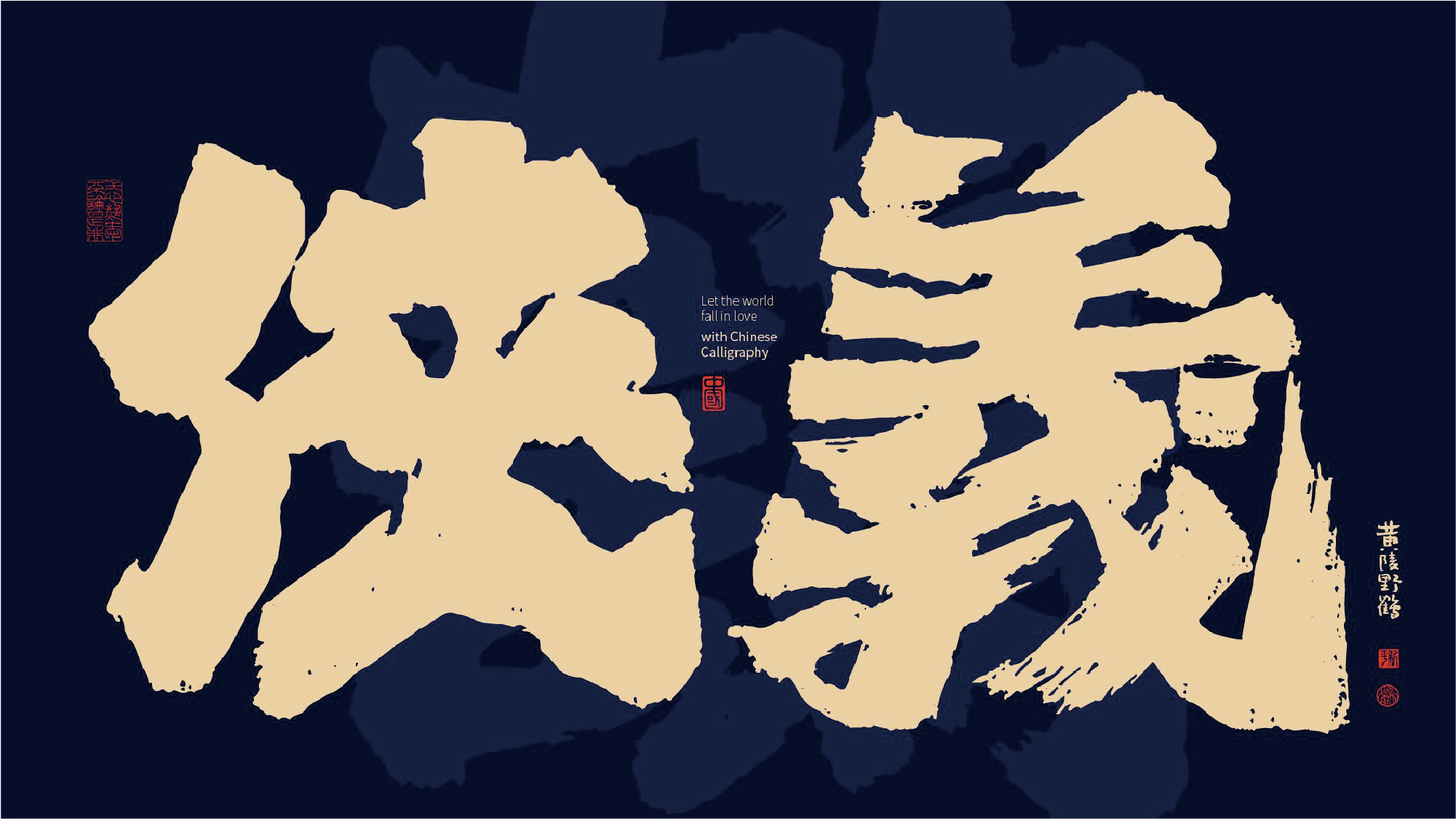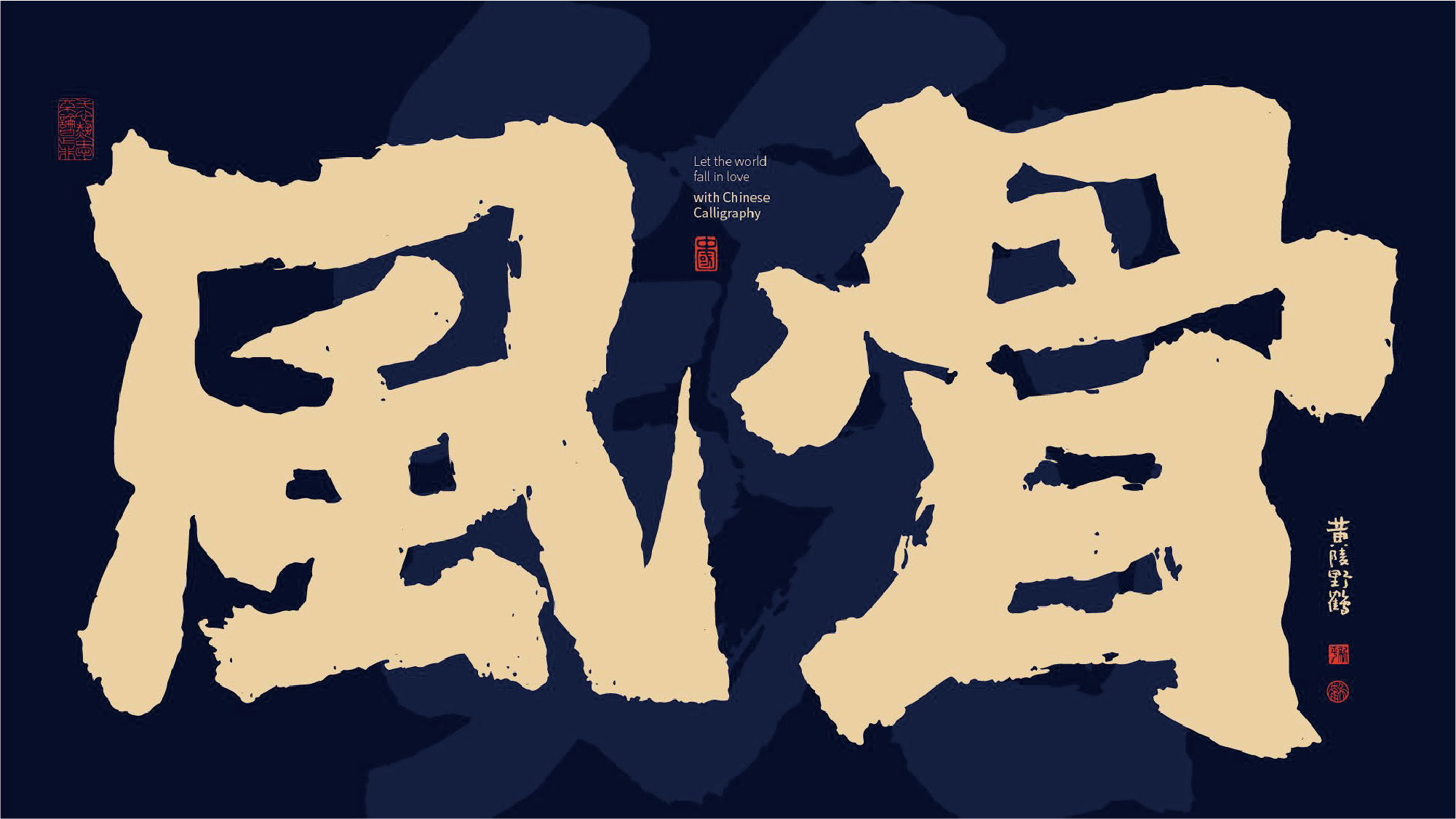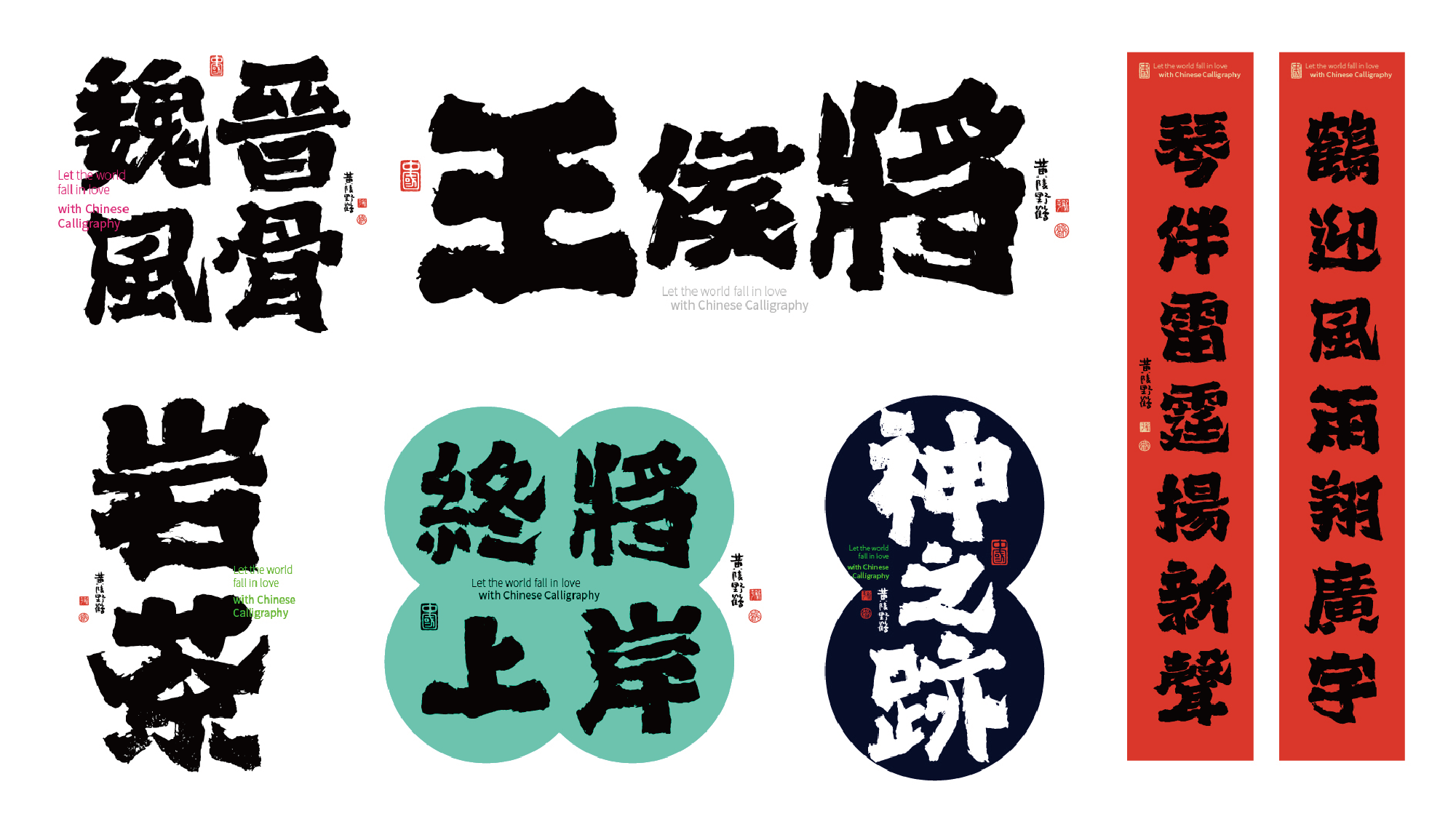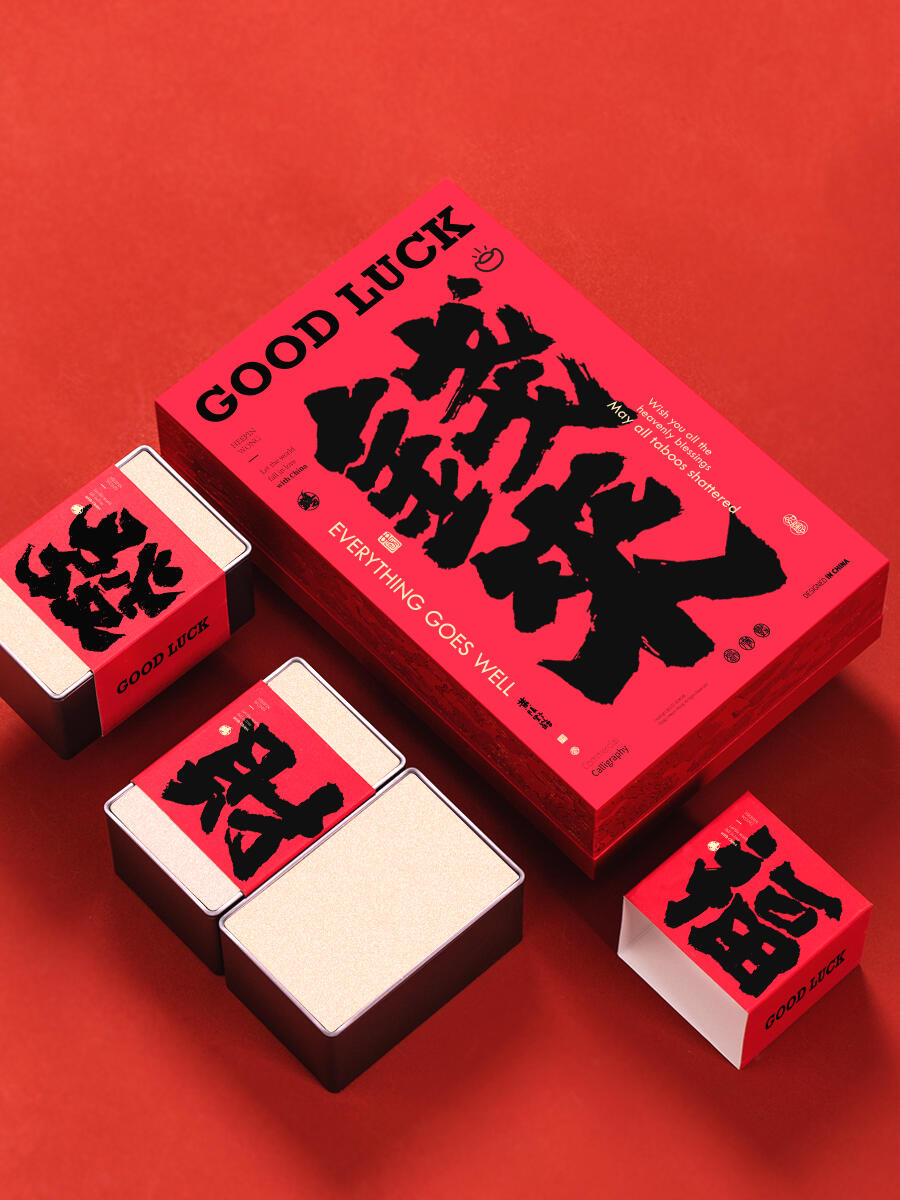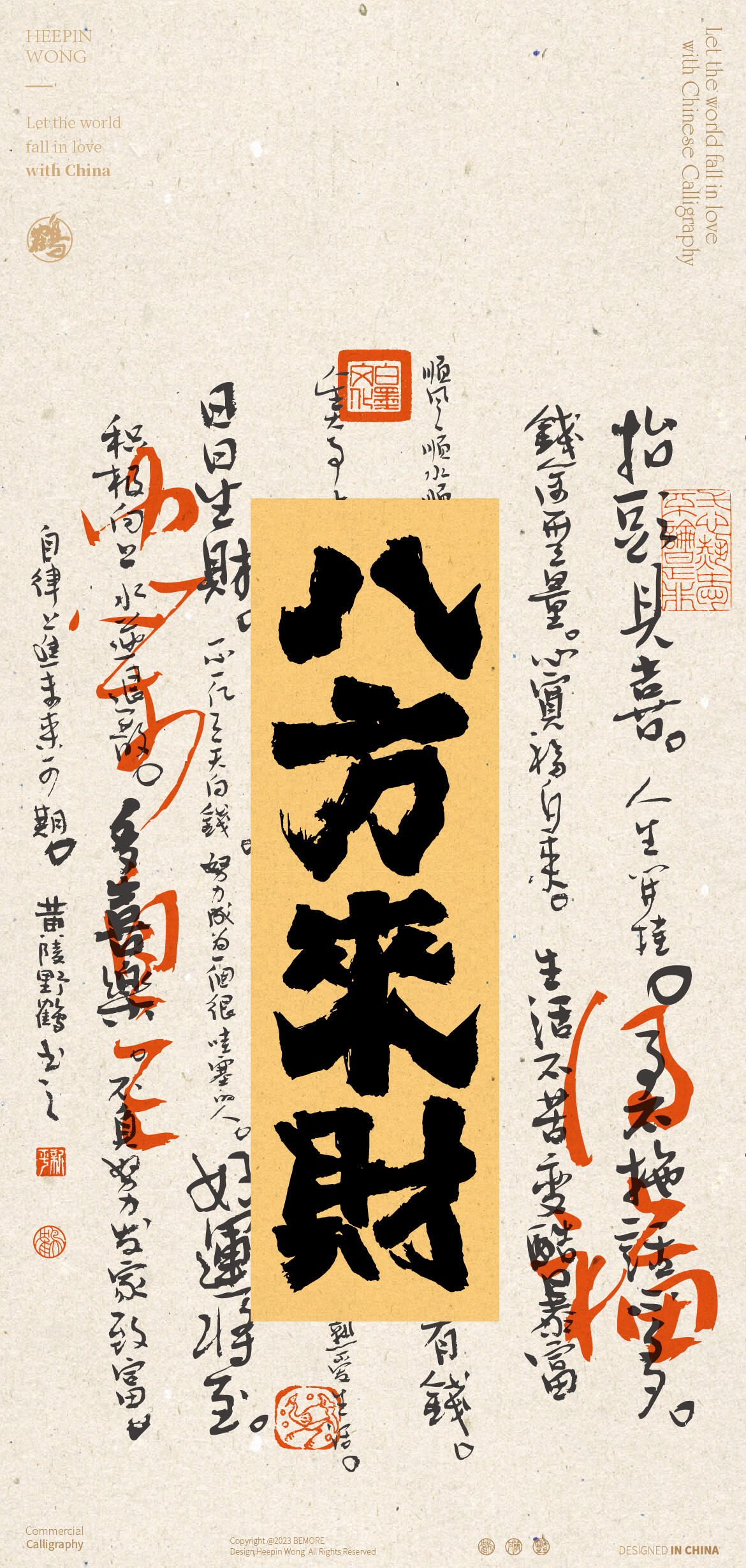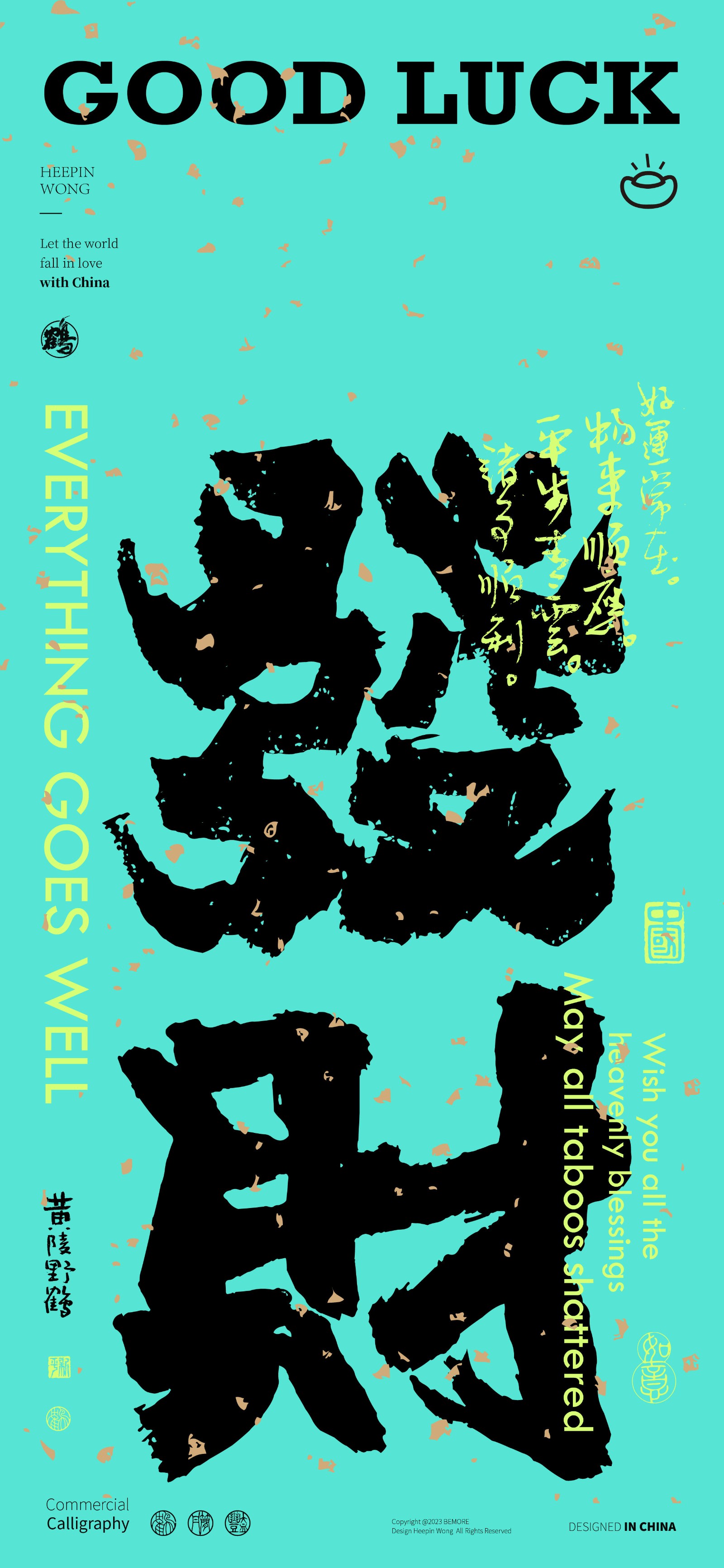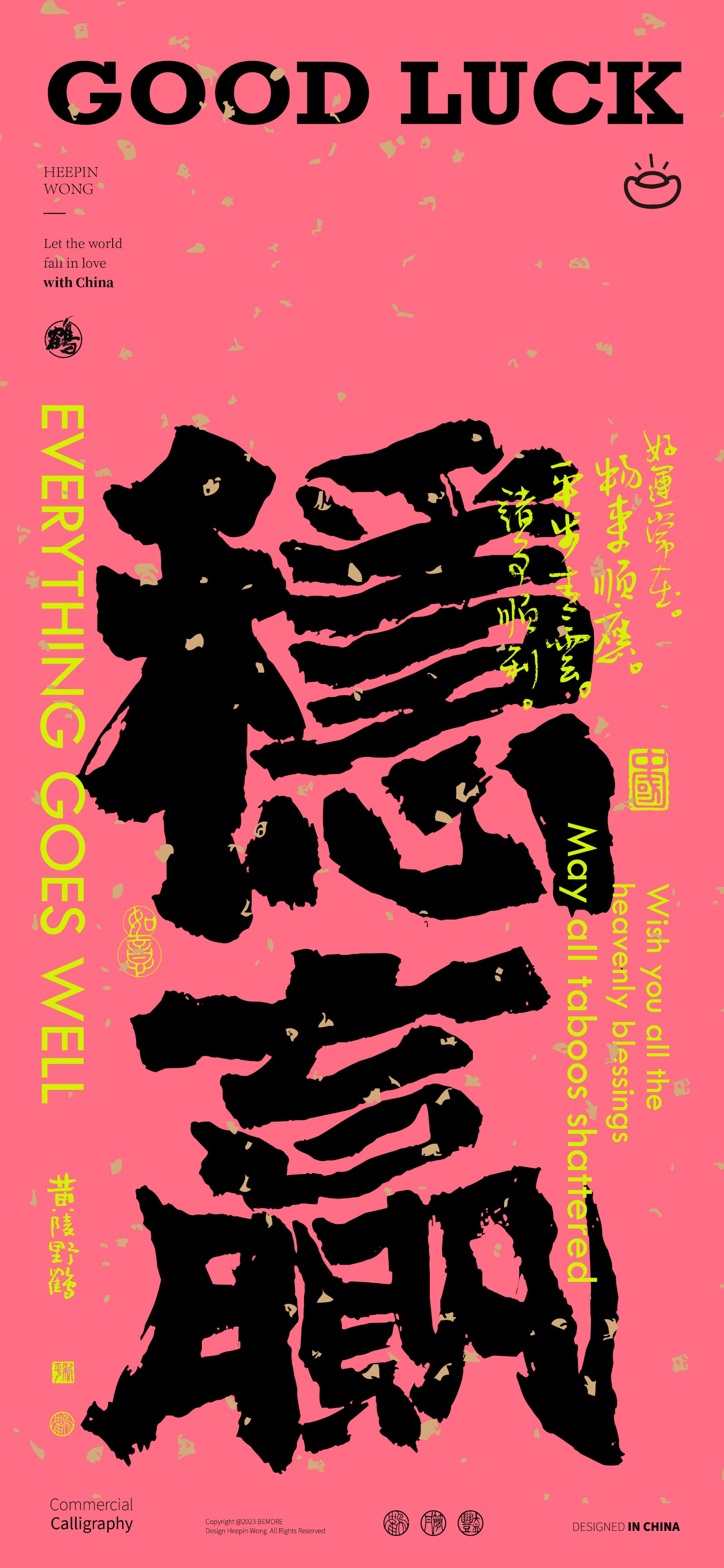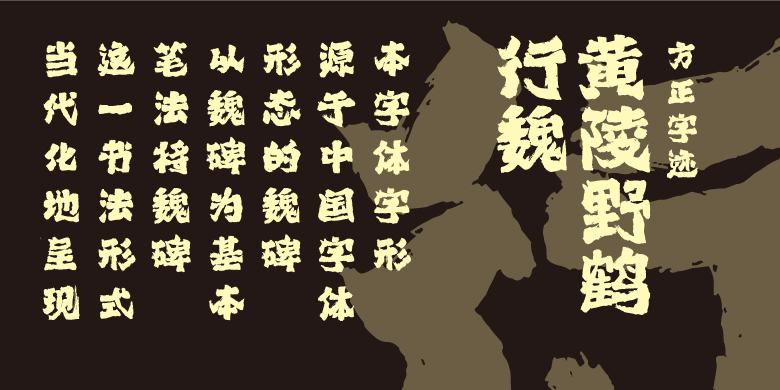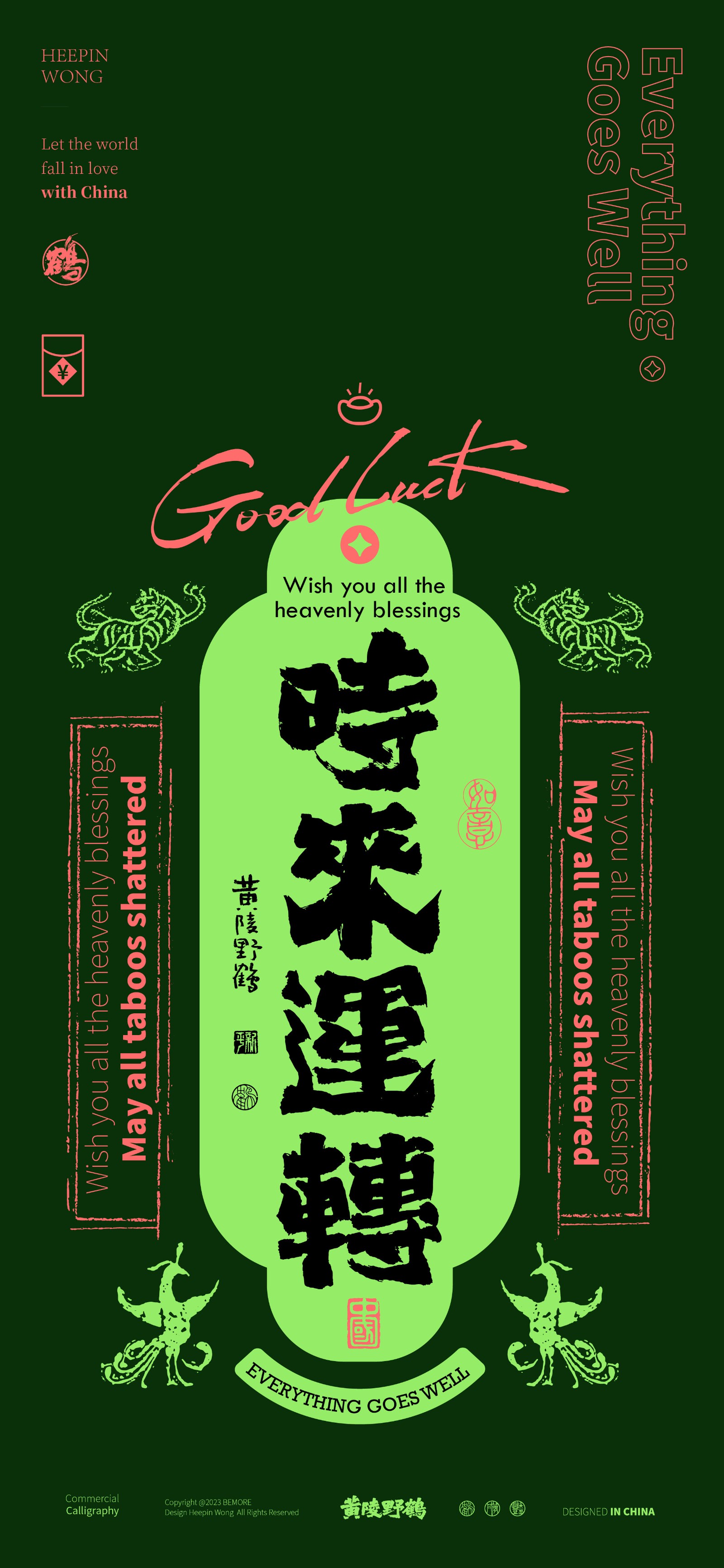
方正字迹-黄陵野鹤行魏
字体品牌: 方正字迹 设计师:黄新平 字体分类:创意书写 字体属性:精品字 字符集:大陆简体(GB2312-80)、简繁扩展(GBK) 发布时间: 2024
黄陵野鹤行魏,本字体字形源于中国字体形态的魏碑,以魏碑为基本笔法,将魏碑这一书法形式当代化地呈现。旨在能够将魏碑这一书法形式更广泛地应用到生活中。另外本字体在传统魏碑形态的基础上加入了现代设计需求的夸张笔意,让本字体既能够传承魏碑这一字体的美学形态,又能够更好地符合于当下的设计应用。
以笔代刀,书写魏晋风流;笔墨之间,挥洒江湖豪情。方正字迹-黄陵野鹤行魏由墨研社创始人黄新平(黄陵野鹤)书写,字体融合了经典魏碑书法的字形与笔法,将魏碑进行现代化呈现,旨在能够将魏碑这一书法形式更广泛地应用到生活中。
魏碑是中国南北朝时期北朝文字刻石的通称,以北魏为最精。魏碑风格多样,朴拙险峻,舒畅流丽。魏碑上承汉隶传统,下启唐楷新风,为现代汉字的结体、笔法奠定了坚实的基础。方正字迹-黄陵野鹤行魏的字形源于魏碑,在继承魏碑笔法精髓的同时,进行了大胆的创新与突破,创作出一款符合现代国潮审美意趣的创意手书。
方正字迹-黄陵野鹤行魏在传统魏碑字体形态的基础上,加入受现代设计师青睐的夸张笔意,使该字体既能传承传统魏碑的美学形态,又更加符合当下的设计应用需求。
方正字迹-黄陵野鹤行魏风格饱满雄强,朴拙险峻,大字排版时气势磅礴、醒目有力,字里行间散发出浓浓的中国气韵。